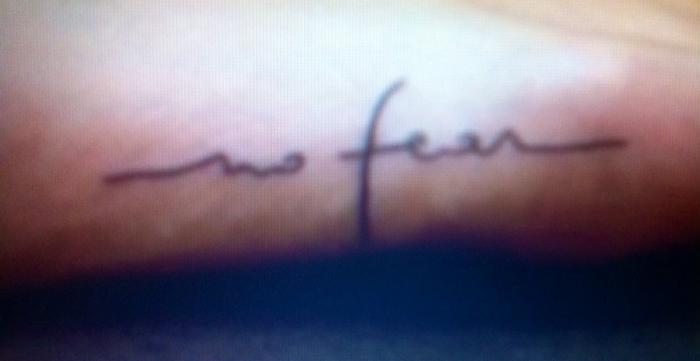
Gerade Tattoo-Künstler pfeifen zumeist auf auf Schriftarten mit Namen, und zeichnen so etwas freihändig, so lässt sich das viel besser an die Zielposition anpassen. (Obwohl ich durchaus von 2 meiner Schriften schon Tattoos gesehen habe, bzw. einen Text auf Basis einer meiner Schriften für diesen Zweck um gezeichnet habe - die ist dann allerdings auch nicht mehr völlig erkennbar.
Ich dachte mir auch, dass das eine Handschrift ist. Dachte aber, dass es eventuell eine Schriftart gibt, die so ähnlich aussieht.